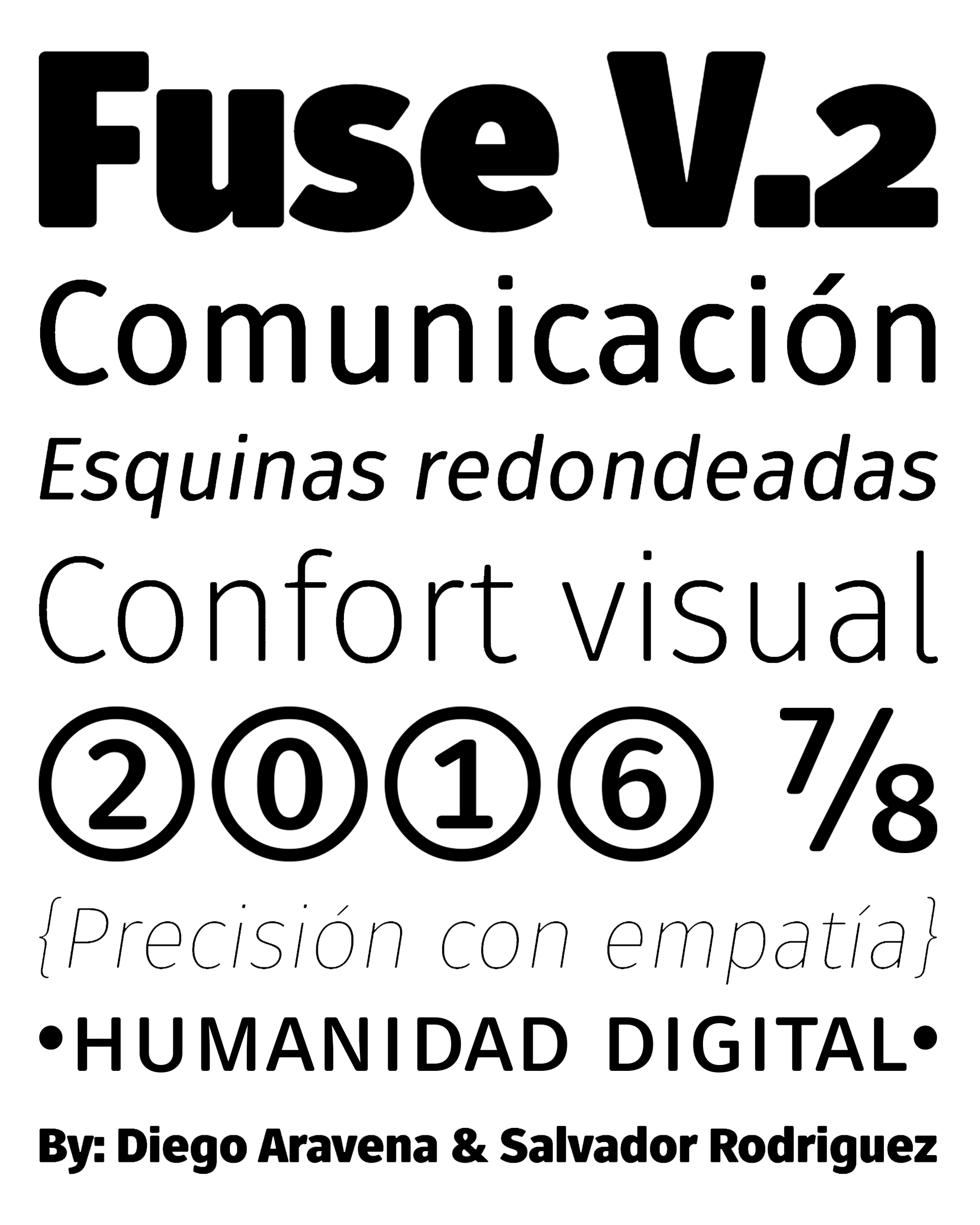
| Créditos | Diego Aravena, Salvador Rodríguez |
| Descripción | Fuse Vol. 2 es una extensión de nuestra popular familia tipográfica Fuse. Todos los vértices de los caracteres han sido redondeados, lo que convierte a Fuse Vol. 2 en una variante más amigable y cercana de la Fuse original. |
| Familia(s) | Fuse, Fuse V.2 Display Thin, Fuse V.2 Display Thin Italic, Fuse V.2 Display Ultralight, Fuse V.2 Display Ultralight Italic, Fuse V.2 Display Light, Fuse V.2 Display Light Italic, Fuse V.2 Display Book, Fuse V.2 Display Book Italic, Fuse V.2 Display Regular, Fuse V.2 Display Regular Italic, Fuse V.2 Display Bold, Fuse V.2 Display Bold Italic, Fuse V.2 Display Extrabold, Fuse V.2 Display Extrabold I |
| Fundidora | W Type Foundry |